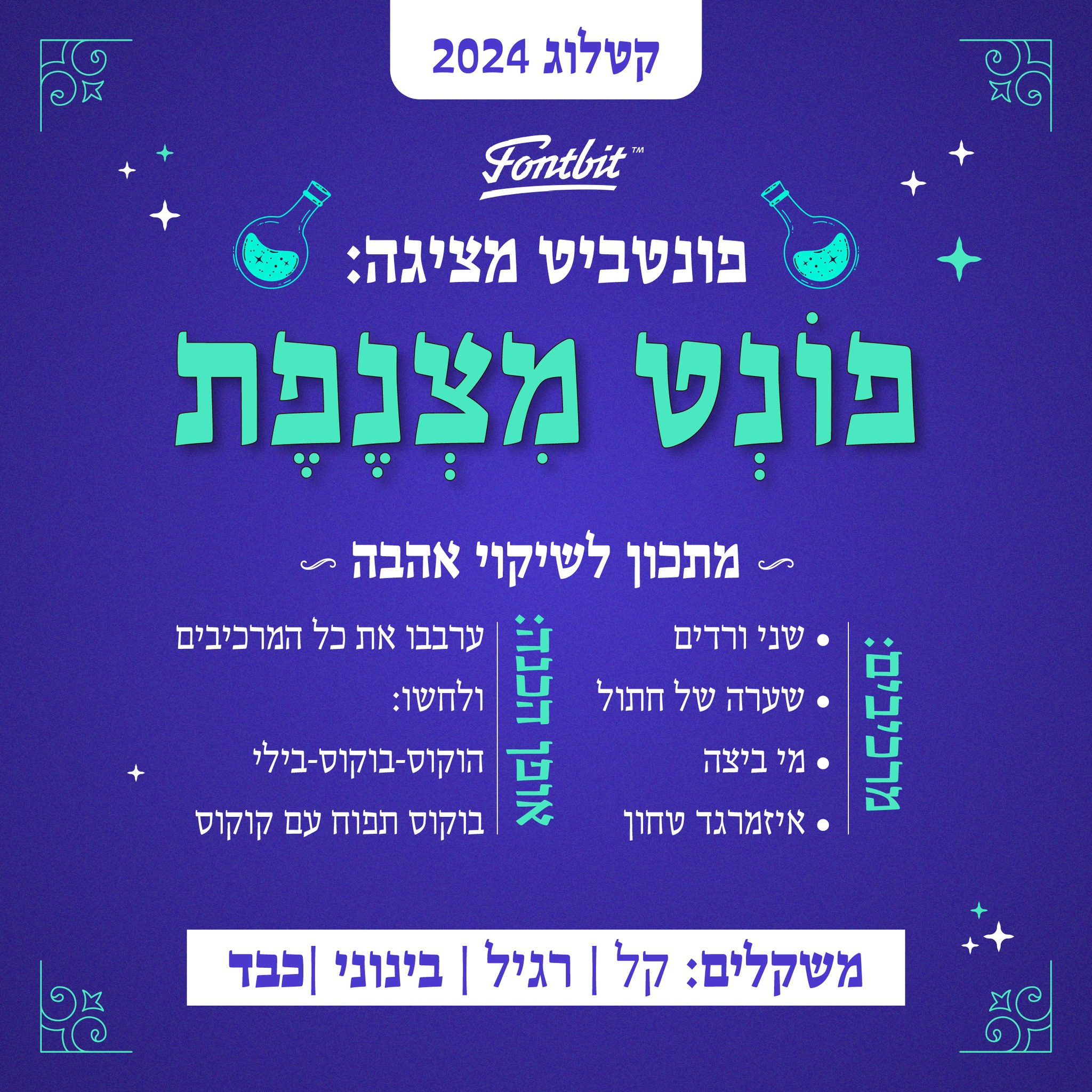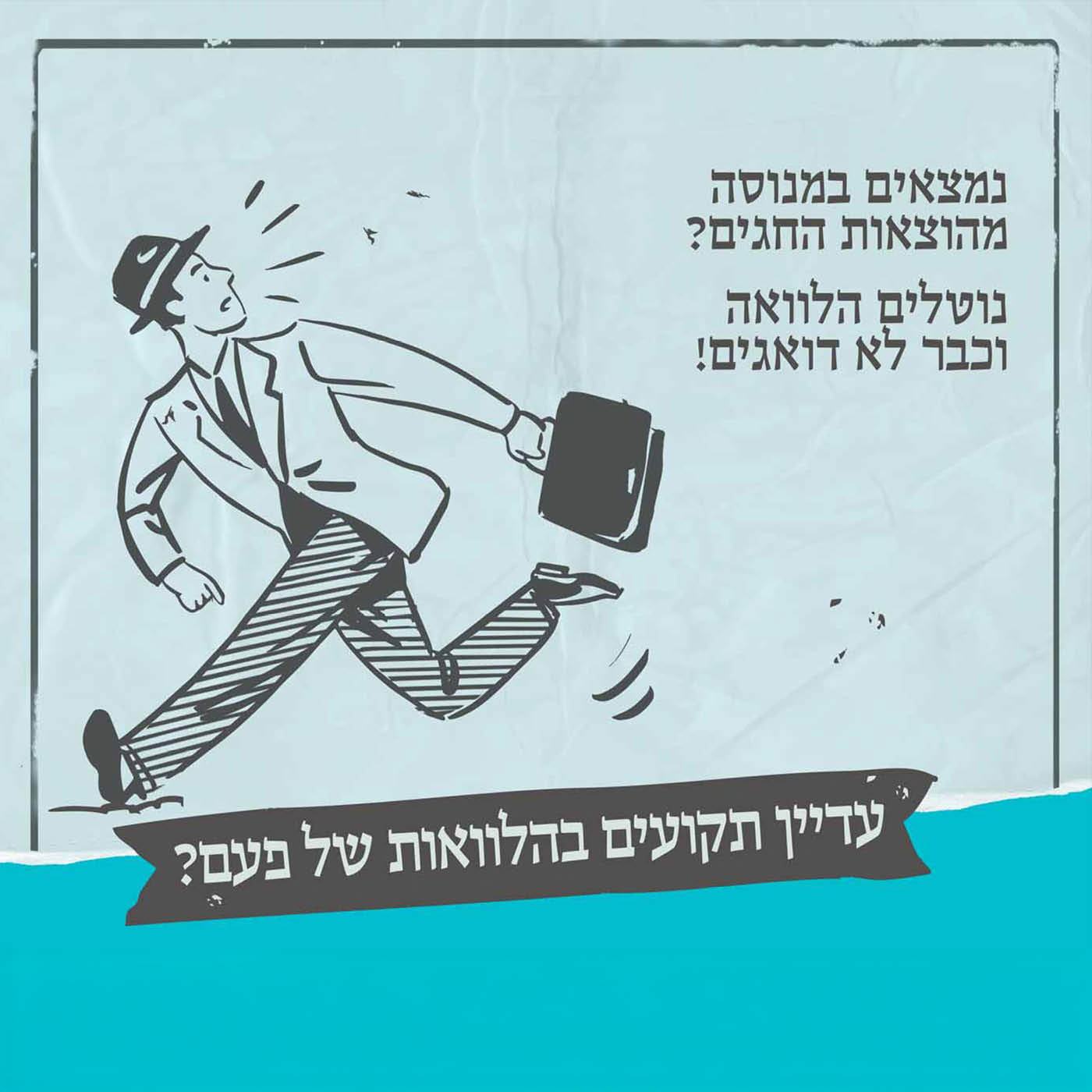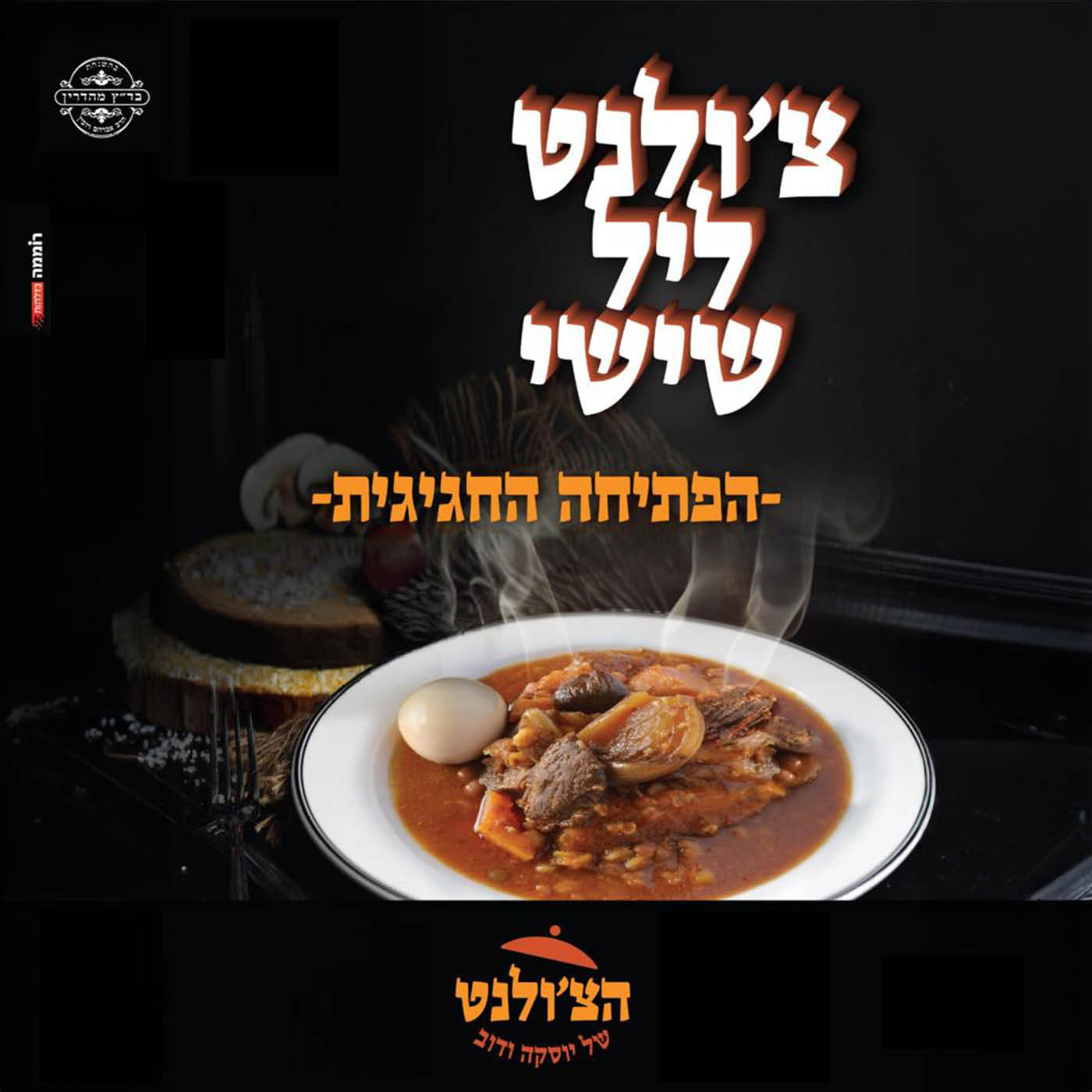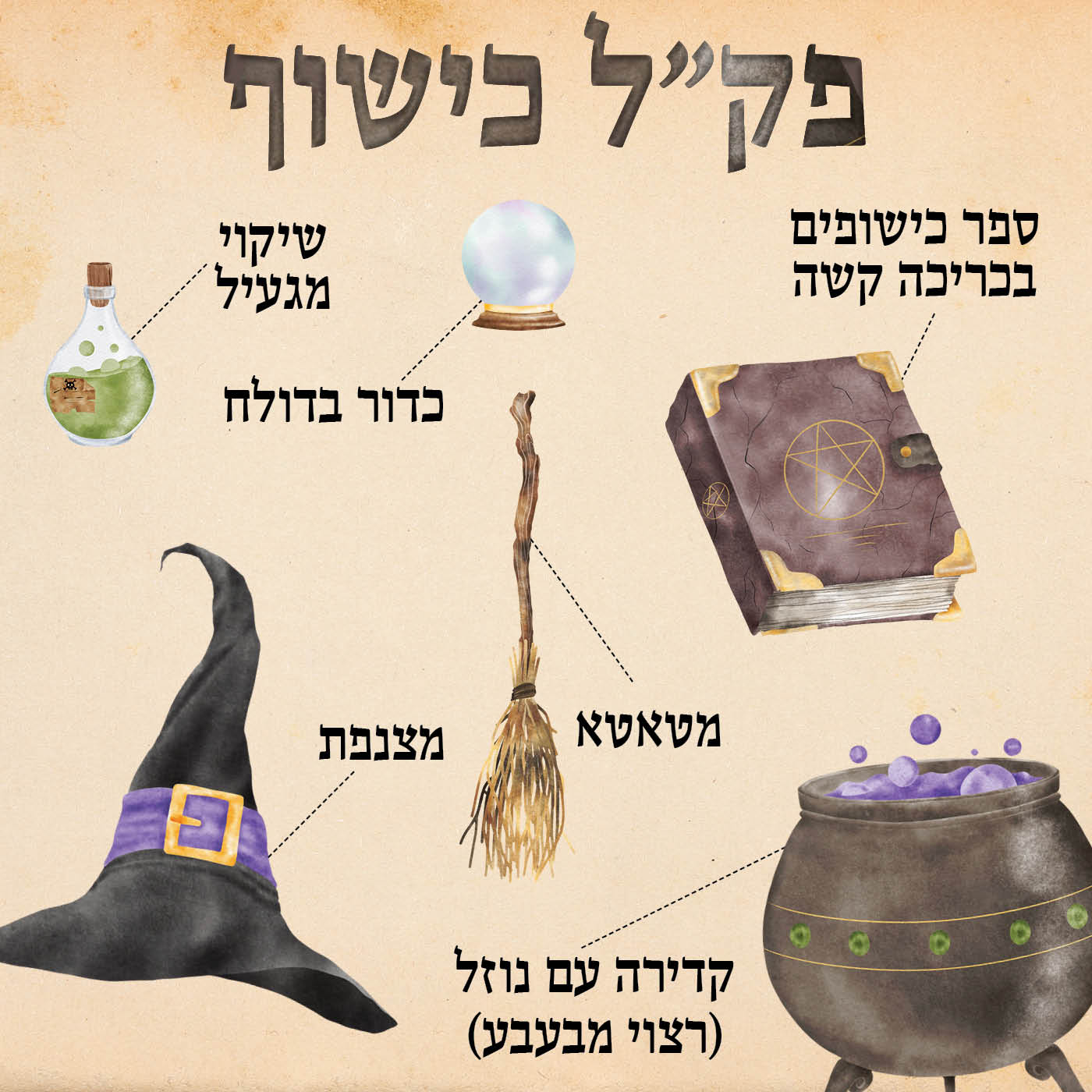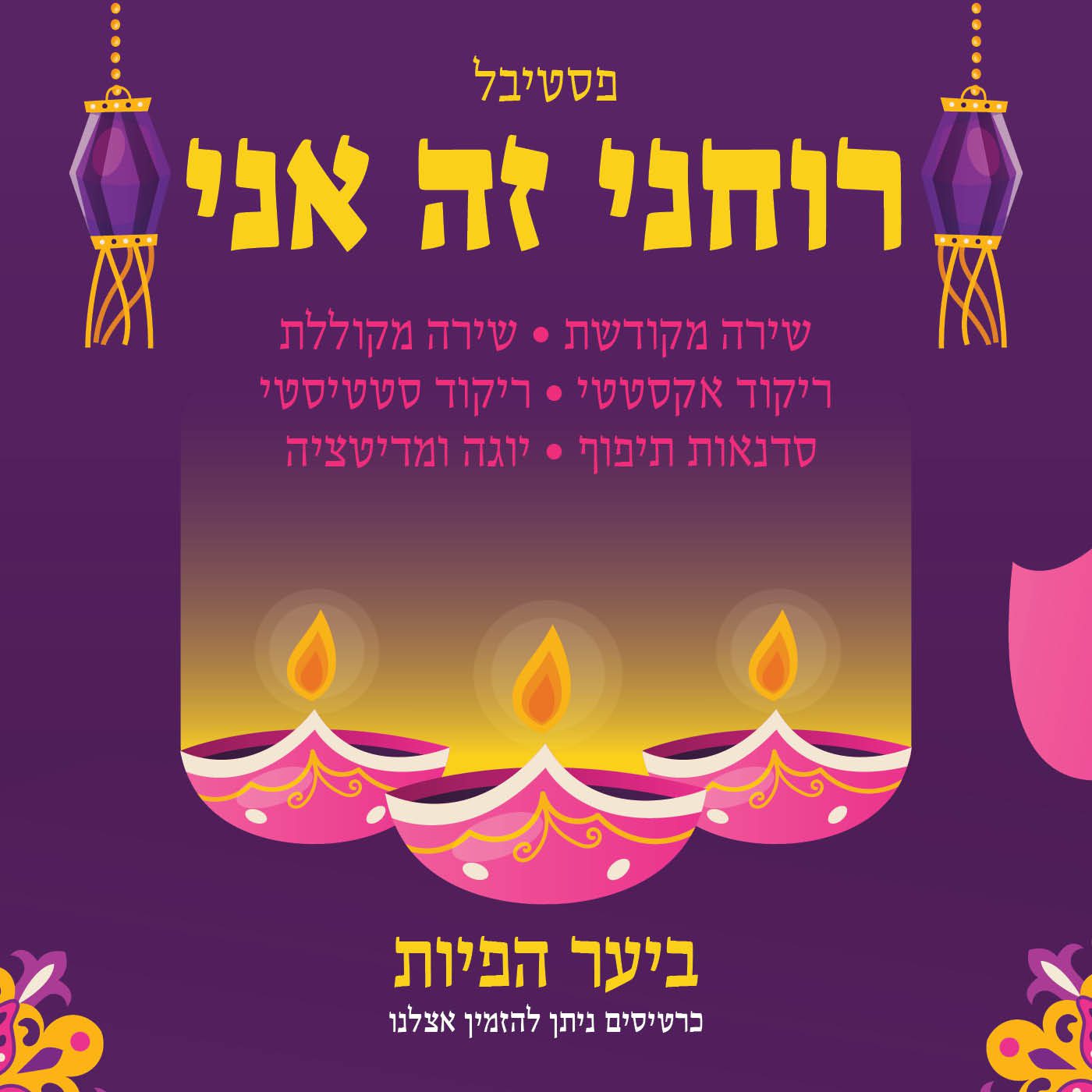
מצנפת
מצנפת / Miznefet
• שם הגופן:מצנפת
• מעצב הגופן:נדב עזרא
• סגנון:סריף
• מאפיינים: קל רגיל בינוני כבד
• תכונות: אוונגרדי אקזוטי חושני משולש מתוק נוסטלגי רוחני שמח
סיפור הגופן:
ההשראה לפונט נלקחה מפוסטר של להקת ״החלונות הגבוהים״. ל״מצנפת״ הרגשה של חופש ושובבות, מה שמעניק לו מראה מיוחד שמגיע היישר מהאגדות, זה גופן עם המון תעוזה ודמיון. הוא מתאים לעיצוב ספרי ילדים, סיפורים קסומים על מכשפות וספרי פנטזיה. אבל לא רק! המראה השובבי שלו מתאים למגוון עיצובים. נסו ותיהנו!